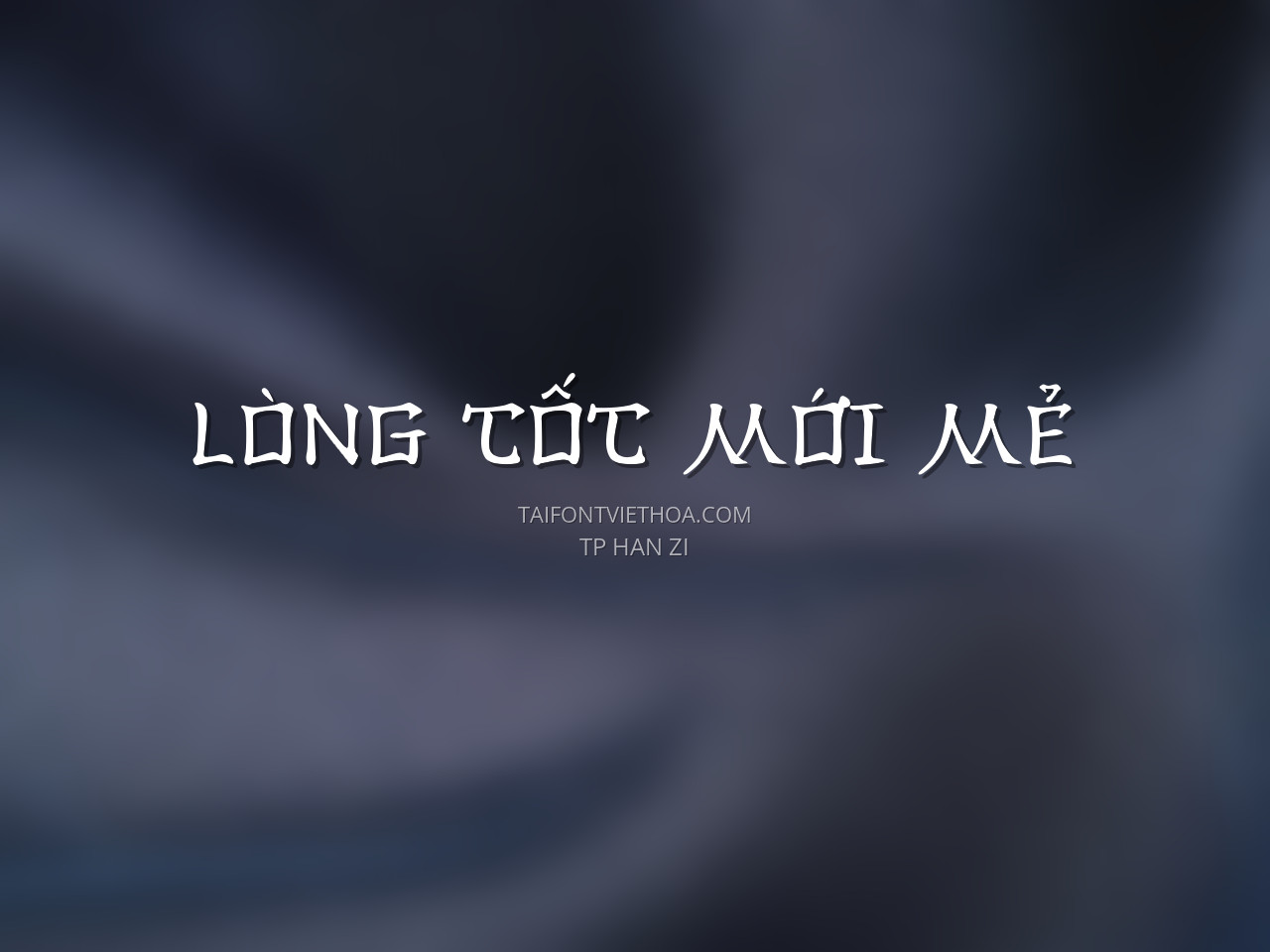
Font việt hóa TP Han Zi phong cách Nhật Bản
Giới thiệu về font TP Han Zi Phong Cách Nhật Bản – Kiểu chữ decorative mang đậm nét văn hóa và nghệ thuật Nhật Bản
TP Han Zi Phong Cách Nhật Bản là phiên bản Việt hóa của font Han Zi – một kiểu chữ decorative lấy cảm hứng từ phong cách truyền thống và hiện đại của Nhật Bản. Font được thiết kế với các nét chữ độc đáo, sắc nét và mang đậm dấu ấn văn hóa, phù hợp cho các dự án thiết kế poster, banner, thương hiệu và các sản phẩm truyền thông mang phong cách Á Đông.
Phiên bản Việt hóa của TP Han Zi Phong Cách Nhật Bản đã được Taifontviethoa.comchăm sóc kỹ lưỡng, hỗ trợ đầy đủ dấu tiếng Việt cùng nhiều ngôn ngữ khác. Font giúp các nhà thiết kế dễ dàng áp dụng trong các dự án sáng tạo đậm chất văn hóa và nghệ thuật.
Thiết kế decorative độc đáo – Lý tưởng cho dự án văn hóa và nghệ thuật
TP Han Zi Phong Cách Nhật Bản sở hữu các nét chữ sắc nét, có cấu trúc rõ ràng và tinh tế, tạo cảm giác trang trọng, đặc trưng và thu hút. Font rất phù hợp cho tiêu đề, logo, poster hoặc các phần thiết kế cần điểm nhấn mang đậm nét văn hóa và nghệ thuật truyền thống Nhật Bản. Phong cách thiết kế của Han Zi rất thích hợp với các dự án phim ảnh, sự kiện văn hóa, quảng cáo và nghệ thuật.
Ứng dụng lý tưởng: thiết kế poster phim, banner sự kiện văn hóa, thiệp mời, logo thương hiệu nghệ thuật và các dự án sáng tạo cần phong cách đặc trưng và trang trọng. Ngành nghề phù hợp: văn hóa, nghệ thuật, phim ảnh, sự kiện, quảng cáo và truyền thông.